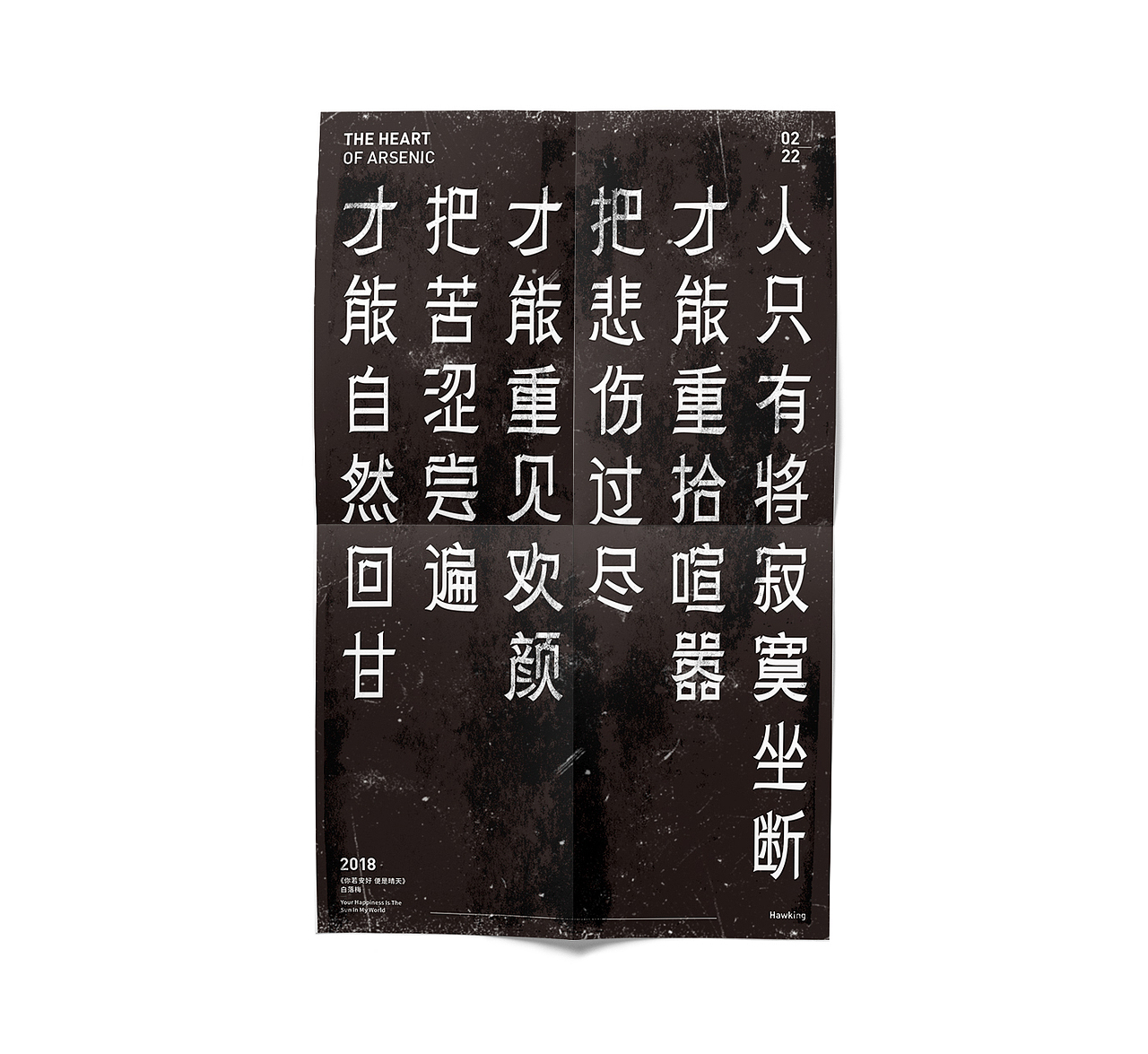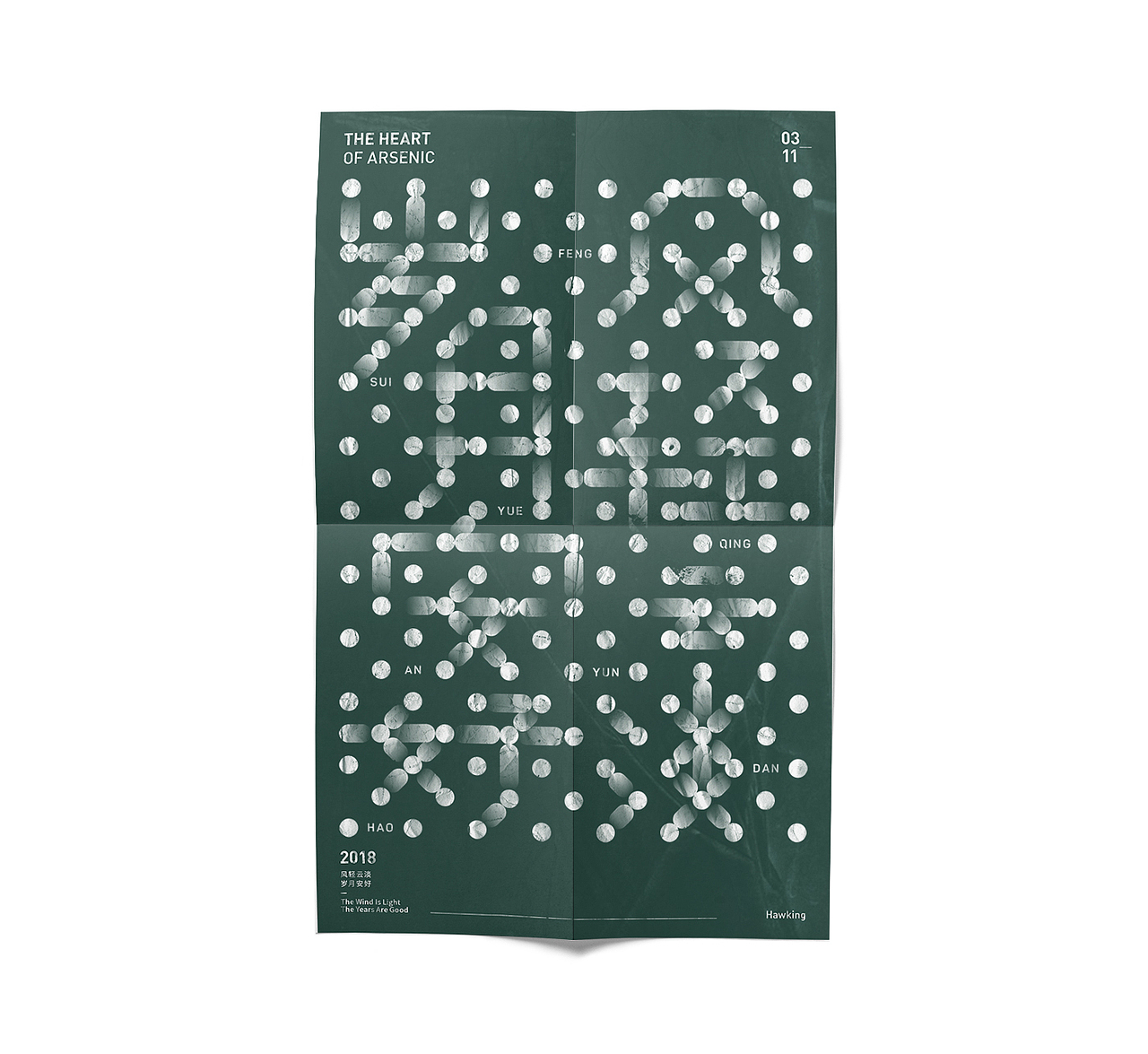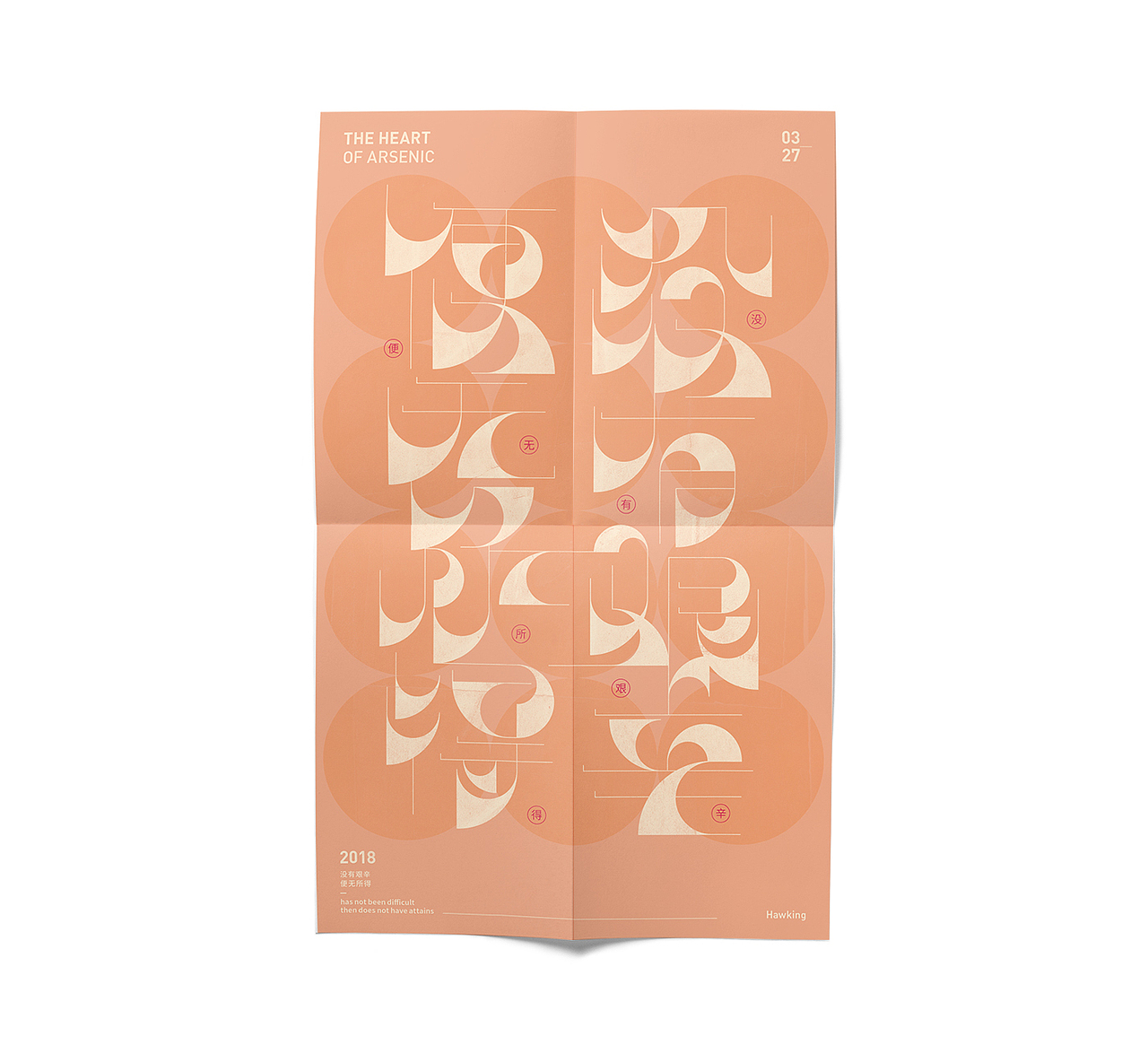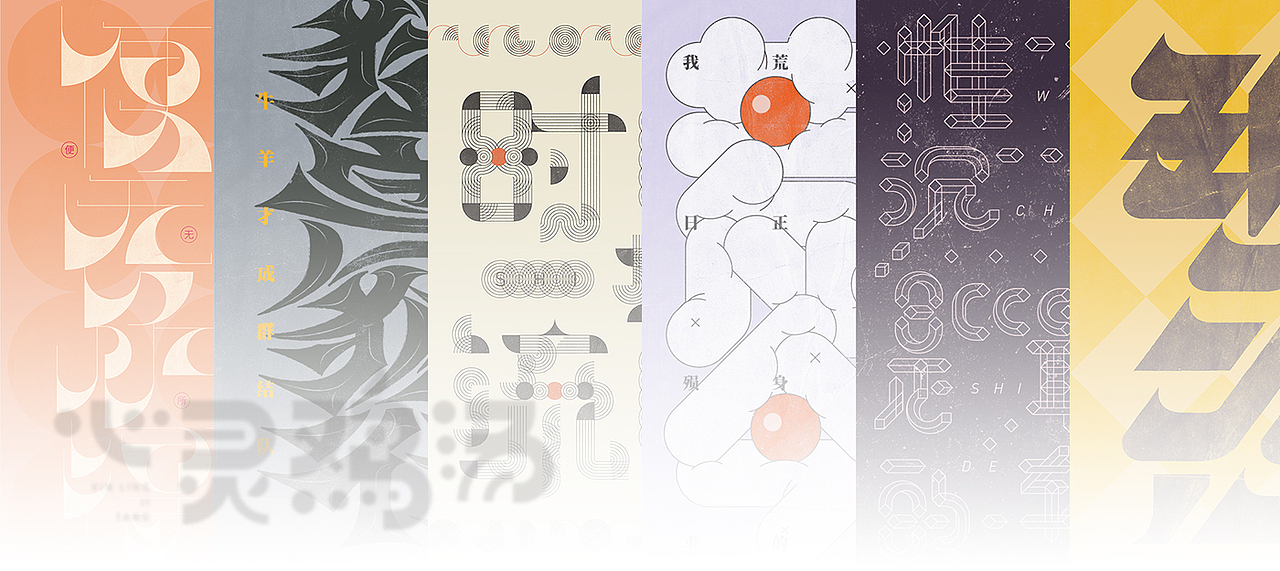
心灵鸡汤
去年经过了一段昏暗的日子,才深刻理解了人生苦短,最起码还活着,还能做我热爱的事,足矣。
今年年初重新开始作字,尝试以海报的形式将纯粹的字形展示出来,
中途3月14日突然得知霍金去世的消失,一时不敢相信,因为您在我心目中永远是一座坚实的靠山,每当心态爆炸的时候,总会想到还有一位老者,他将毕生的经历献给了他所热爱的事业,我这点困难算的了什么,收拾好心态重新上路。
当初,发现大牛逼都得有个英文名,那我也的假模假样的装一下,叫什么英文名那?想到了Hawking(霍金),一方面是因为身体状况有些相近,更主要的是希望以此激励自己,从那之后开始坚持作字,我也收获到很多。
真的非常荣欣能与您生活在同一时代!!
回头发现我选的“心灵鸡汤”这个主题也蛮好的,希望大伙坚持你所选择的这条设计之路,珍爱时间,热爱生活。
“鸡汤”食材为:
1、在時間的大鐘上,只有兩個字「現在」 ——莎士比亚
2、猛兽总是独行,牛羊才成群结队。 —— 鲁迅《鲁迅杂文精选》
3、没有艰辛,便无所得。 —— 哈佛图书馆训言
4、我荒废的今日,正是昨日殒身之人祈求的明日。 —— 哈佛图书馆训言
5、时间在流逝 —— 哈佛图书馆训言
6、风轻云淡,岁月安好。 —— 林徽因
7、惟沉默是最高的轻蔑 —— 鲁迅
8、愿你出走半生,归来仍是少年
9、因为爱过,所以慈悲;因为懂得,所以宽容 —— 张爱玲
10、今生今世,我只是个戏子,在别人的故事里,流着自己的泪。 —— 席慕蓉《戏子》
11、人只有将寂寞坐断,才能重拾喧嚣;把悲伤过尽,才能重见欢颜;把苦涩尝遍,才能自然回甘。 —— 林徽因
12、你要做一个不动声色的大人了。不准情绪化,不准偷偷想念,不准回头看。去过自己另外的生活。你要听话,不是所有的鱼都会生活在同一片海里。 —— 村上春树《舞!舞!舞!》
在時間的大鐘上
只有兩個字「現在」
猛兽总是独行
牛羊才成群结队
没有艰辛
便无所得
我荒废的今日
正是昨日殒身之人祈求的明日
时间在流逝
风轻云淡
岁月安好
惟沉默是最高的轻蔑
愿你出走半生
归来仍是少年
因为爱过 所以慈悲
因为懂得 所以宽容
今生今世 我只是个戏子
在别人的故事里 流着自己的泪
人只有将寂寞坐断,才能重拾喧嚣;
把悲伤过尽,才能重见欢颜;
把苦涩尝遍,才能自然回甘
你要做一个不动声色的大人了。
不准情绪化,不准偷偷想念,不准回头看。去过自己另外的生活。
你要听话,不是所有的鱼都会生活在同一片海里。